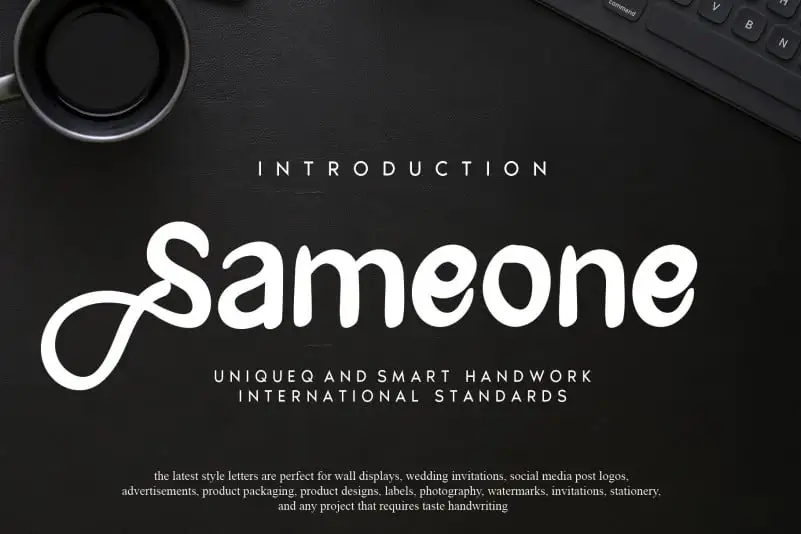
A Fonte ‘Sameone Script’ é uma elegante e simpática fónta escrita a mão. Seu estilo natural e único se torna perfeitamente adequado para um vasto número de projetos gráficos. Com seu design suave e autêntico, ela se destaca como uma opção ideal para aqueles que buscam um toque humano em seus designs digitais. Seu designer, Andikastudio, criou um material visual único e memorável, sem limites à imaginação dos designers. Seja você o gráfico mais audacioso ou quem busca uma fónta delicada, ‘Sameone Script’ oferece a liberdade para explorar seus ideais e transformá-los em arte digital.